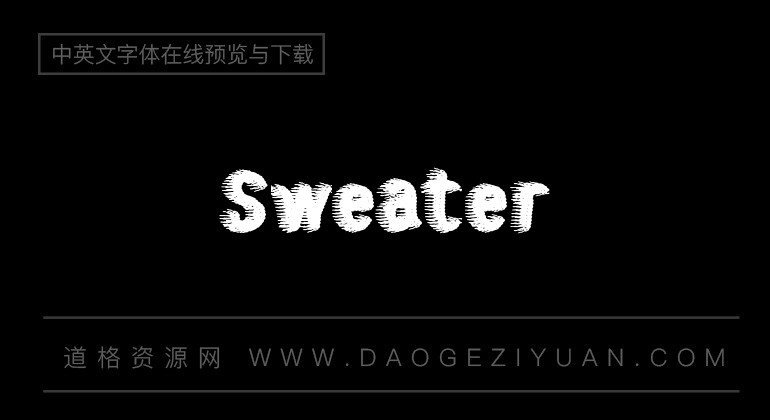
Sweater 是一款温暖的英文字体,它的字形设计灵感来源于经典的美国字体,采用细腻的线条、结实的笔画、以及丰富的字形特征,打造出一款充满温暖感的英文字体。它的字体特点是有趣而又充满活力,可以搭配简洁的英文文字,给人一种温暖而又活泼的感觉。内容介绍
Sweater是一款非常不错的手写艺术字体,具有很好的视觉感,适合于文化类的宣传设计、商业类品牌的广告和产品包装设计以及个性化文字排版等较多场景。